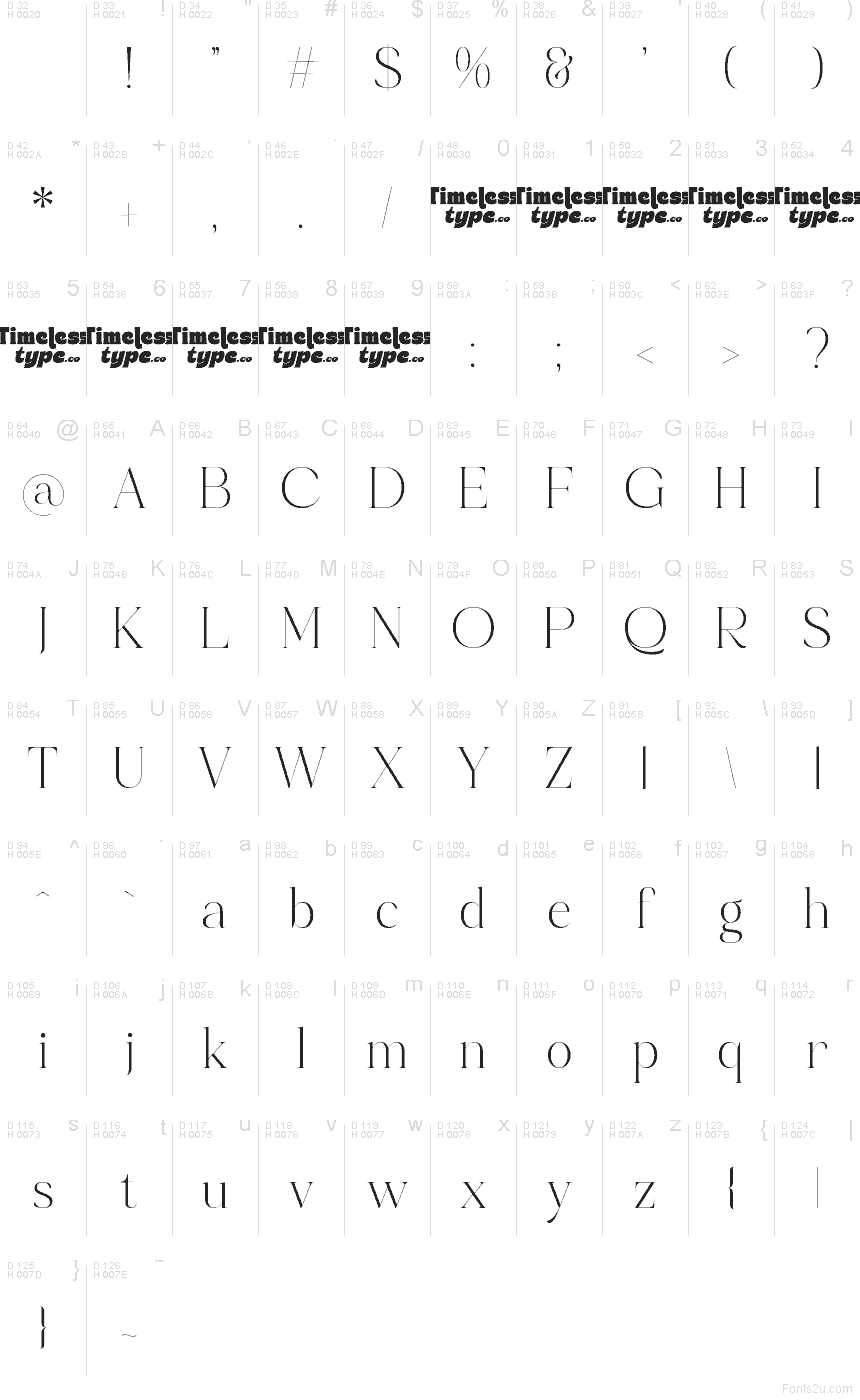
Perfect Romantic od TimelessType to bezpłatny, kontrastowy krój szeryfowy w romantycznym stylu, inspirowany modą i delikatną kaligrafią. Litery łączą cienkie linie z szerokimi łukami i subtelnymi zawijasami, dzięki czemu font sprawia wrażenie pełnego gracji i lekkości, a nie surowości.
Świetnie sprawdzi się w brandingu, opakowaniach kosmetyków, papeterii ślubnej, nagłówkach czasopism oraz szyldach butików – wszędzie tam, gdzie potrzebujesz darmowego fontu o eleganckim wyrazie, który nie jest przesłodzony. Wysokie litery i ozdobne pętle idealnie nadają się do krótkich tytułów, monogramów i inicjałów, gdzie te płynne krzywizny mogą w pełni pokazać swój charakter.